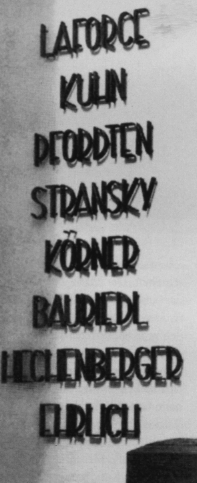
Hilfe: Schrift gesucht?
vielleicht kann mir wer von euch helfen diese Schrift zu identifizieren, oder zumindest eine die dieser hier ähnlich sieht:
die Angostura sieht ihr schon recht ähnlich, aber ein bisschen exakter könnts noch werden.
Aber das ist doch die Angostura von Ray Larabie?
Die Angostura hat sich vielleicht im Laufe der Zeit gewandelt? Ich gehe zumindestens davon aus und würde mal nach den verschiedenen Jahrgängen schaun. Und nach der alten, aber freien Version die seit 10 Jahren durchs WWW geistert. Siehe: http://www.abstractfonts.com/font/5195
Das Suchen in MyFonts scheint bei dieser Schrift nicht zu klappen ... :-o
Das schrieb er doch dass das die Angostura ist. Er sucht die Schrift aus dem Bild darüber.